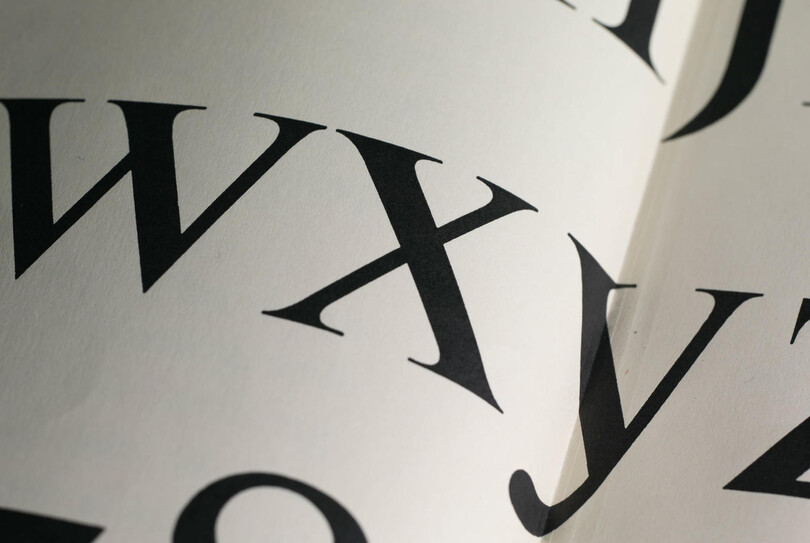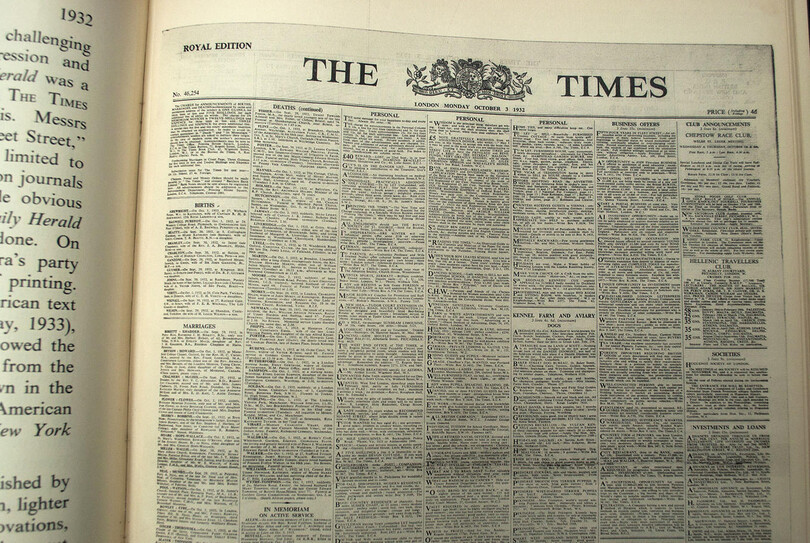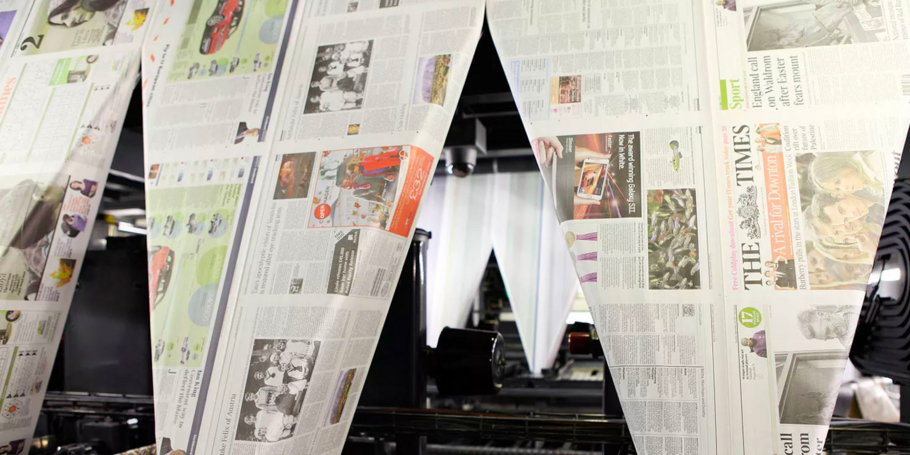
Times Modernと現代
ビジネス上でテキストを印刷する場合、どのフォントを使用するかは非常に重大なことです。1932年のTimes New Roman®フォントの導入から現在のTimes Modernフォントに至るまで、The Times紙で使用するフォントは、The Times紙ブランドの重要かつ象徴的な要素でした。
書体を話題にするときは、細かいディテールに焦点が絞られる傾向がありますが、ここでは書体のライフサイクルについてお話しします。具体的には、この書体がどのようにして、ロンドンのThe Times紙にとって重要な役割を占めるようになったかについて説明します。The Timesは何十年にもわたり利用されてきた信頼のブランドフォントです。
The Timesの背景
この話は1930年に始まります。Stanley Morisonが、The Times紙の版元に対して新聞での書体の利用について厳しい批判を書いたことに端を発します。イギリスのMonotypeの書体アドバイザーであるMorisonは、さまざまな一般的Caslon™スタイルを使用していることで、The Timesの権威と名声が傷つけられていると警告しました。
Caslon™スタイルは、新聞の優れた印刷品質が生かされる書体ではなく、歴史を尊重しつつ、時代の最先端であることを誇る紙面ではやや古臭い印象を与えるフォントでした。
Morisonは、これらのスタイルに代わって、記事の内容を強調したり、視覚的にも編集面でもThe Timesの精神を伝えることができる書体の品質について説明しました。これは、The Timesの意識的なフォントブランディングの始まりでした。
Times New Romanフォントが、実際には1930年代のThe Times紙のためにデザインされたカスタム書体に基づいていることを知っている人はほとんどいません。
The Timesにとって、歴史と現代的なものを融合するスタイルは、1930年代においても、今日においても変わりません。
The Timesは、1785年の創刊以来(当時の名称はThe Daily Universal Register)非常に長く親しまれている新聞です。The Timesは、1932年10月3日にイギリスの新聞において記録的な事柄を成し遂げたことを誇りに思っています。この日、Morisonの指示の下でMonotypeによって制作された斬新でモダンなバナーや新しいフォントファミリーにより、The Timesの古臭い外観が刷新されました。伝統を尊重すると同時に、斬新でモダンなスタイルを追求した結果、Times New Romanフォントが誕生しました。
しかし、多くの人々、特にイギリス国外の人々は、The Timesの新しい書体であることからTimes New Romanという名前が付いたという事実を知りません。
Times New Romanのカスタムフォントの登場後、Times New Romanが使用されている1930年代のThe Times紙面
Times New Romanは、Times New RomanがThe Times紙の独占的財産であった短期間の間に成功を収めました。さらに、Monotypeが他の顧客やフォントメーカーにTimes New Romanを導入すると、その他の顧客やフォントメーカーにも大きな成功をもたらしました。
現在、Times New Romanフォントの普遍性は、多くのメディアにおいて、さまざまな形式で多用されており、The Timesそのものより大きいブランドであるといえます。
Alexander S. Lawson氏は、有名な自身の著書「Anatomy of a Typeface(書体の解剖学)」の中で、「過去70年間に開発されたすべての書体の中で、Times Romanは20世紀を象徴する書体として最も多用されてきたフォントの1つです。」と記しています。
イギリスのサルフォーズにあるMonotypeアーカイブ(保管所)に保管されているオリジナルのTimes New Romanのスケッチ
The Timesの課題
年月とともに発展を続けるThe Timesでは、変化する制作方法やさまざまな状況に対応するために、フォントを定期的に更新する必要性があることを実感しています。このフォントファミリーの変更のすべての側面で、The Timesの「DNA」が継承されており、The Timesの特徴を忠実に再現する斬新さと権威が表現されています。
これは、2006年にNeville Brodyの研究スタジオが最初にデザインした最新のファミリー、Times Modernにも継承されています(現在はMonotypeによってデザインされたさまざまな新しいウェイトとスタイルを備えている)。Times Modernは、The Timesのもう1つの成功であることが証明されました。
そして、数か月かけてこの新しいデザインを使用し、このフォントがどのように機能するか、現在の課題は何かを確認してから、The TimesはMonotypeにこのファミリーの拡張を依頼しました。
それ以来、Monotypeは、オンラインとオフラインの読者のために印刷版と電子版での連続性を保つよう求められてきました。
The Timesのソリューション
MonotypeのRobin Nicholas、Patrick Giasson、Alice Savoieは、特にディスプレイへの表示のため、非常に幅広いウェイト、さらに、オリジナルのセットには含まれていなかったイタリック体の追加など、このファミリーで新しい方向性を模索しました。
Times Classicは2002年に導入されたファミリーで、依然として本文に使用されていますが、その方向性を決めるのは、より鮮明で最適化されたTimes Modernファミリーです。
この書体により、The TimesではThe Timesのブランドフォントを他のメディアでも利用できるようになりました。これまでの印刷版から移行しつつあるデジタル版は、サービス利用者が増加傾向にあるため、The TimesのiPad版では、書体があらためて重要な要素になっており、印刷紙の外観と内容は入念に管理されています。
The Timesではこれまでの労力を放棄し、読者にアプリでの新しい体験を理解してもらおうとは考えていません。書体の忠実性と品質を保証するために、iPadアプリでは、そのページのJPEGやPDF画像ではなく、実際のフォントを使用しています。テキストでは、文字の向きが垂直から水平に切り替わるときリフローされ、書体の鮮明さと読みやすさが保たれます。
アプリに独自のフォントを埋め込むことで、画面レンダリングでは他のiPadアプリと一貫しているように感じられますが、書体のディテールは紛れもなくThe Timesのものです。